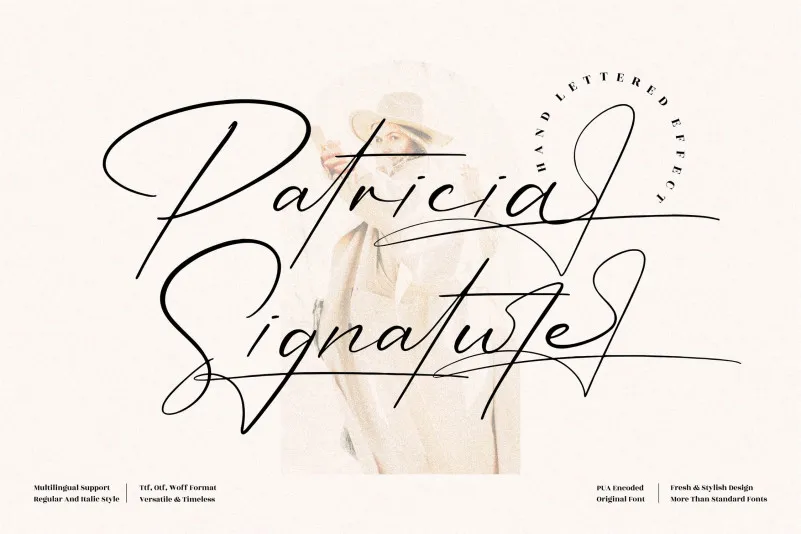
Patricia Signature Font – Download Grátis
A fonte “Patricia Signature” é perfeita para quem busca uma letra elegante e sofisticada que se adequa a projetos variados. Suavemente curvilínea, esta fonte de estilo script não apenas proporciona um toque luxuoso aos seus designs, mas também permite uma vasta gama de aplicação, desde logotipos e identidades corporativas até produtos como mugs e caixas de embalagem personalizados. Além disso, a “Patricia Signature” é perfeita para adicionar um toque de sofisticação em materiais como cartões de nome, convites, cartas de cumprimento e etiquetas. Seja você um designer de moda criando uma capa de livro ou um profissional de publicidade produzindo um logotipo, a “Patricia Signature” oferece um toque único que certamente não vai passar despercebido. Ideal para qualquer projeto onde um toque especial é desejado e valorizado.